주말 다 반납하고 제작한 만화효과음 레이아웃 추출 기능을 대부분 완성했고 반대 작업도 하고 있습니다. 초성, 중성, 종성 한벌만 쓰면 이세상 모든 폰트레이아웃으로 만화효과음 폰트가 그려집니다. 인디자인 대체폰트가 그냥 만들어지기는 하는데 같은 모양이라고 하지 않았습니다. 같은 것도 만들 수는 있지만 일단 그건 예외로 하고
이 결과물은 여러가지 학습결과물로 글자 자소 디자인체계를 바꿀 수 있습니다. 가로, 세로, 모든 획을 구분해서 나눈 다음에 이미지에서 특별한 값을 추출해서 벡터로 깔끔하게 연결하는 Stroke 방식으로 안그려도 대충 그려도 찾아낼 수 있습니다. 각도별로 다 다른 값을 가진 이미지를 생성할 수 있기 때문입니다.
제가 요즘 점선으로 된 무언가를 그리면 외곽이 모두 연결되고 꾸밈하는 글자의 부리. 획의 삐침 등을 색상으로 구분해 두면 그걸 너비에 맞춰서 디자인을 붙여가는 방식을 생각하고 있습니다.
만화효과음은 방향에 따라 다른 느낌을 주기위해 작가가 손을 대는 경우가 많은데 아예 그럴필요없이 방향별로 폰트를 다 생성할 수 있습니다. ttf 나 otf 같은 파일이 아니라 svf 로 만화 그리는 에디터에서 직접 수정하는 것도 가능하게 됩니다.
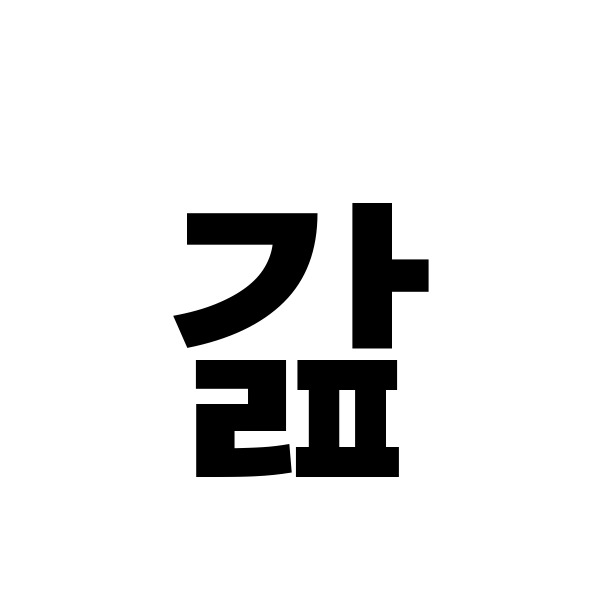
예를 들어 기존 글꼴이 있다면
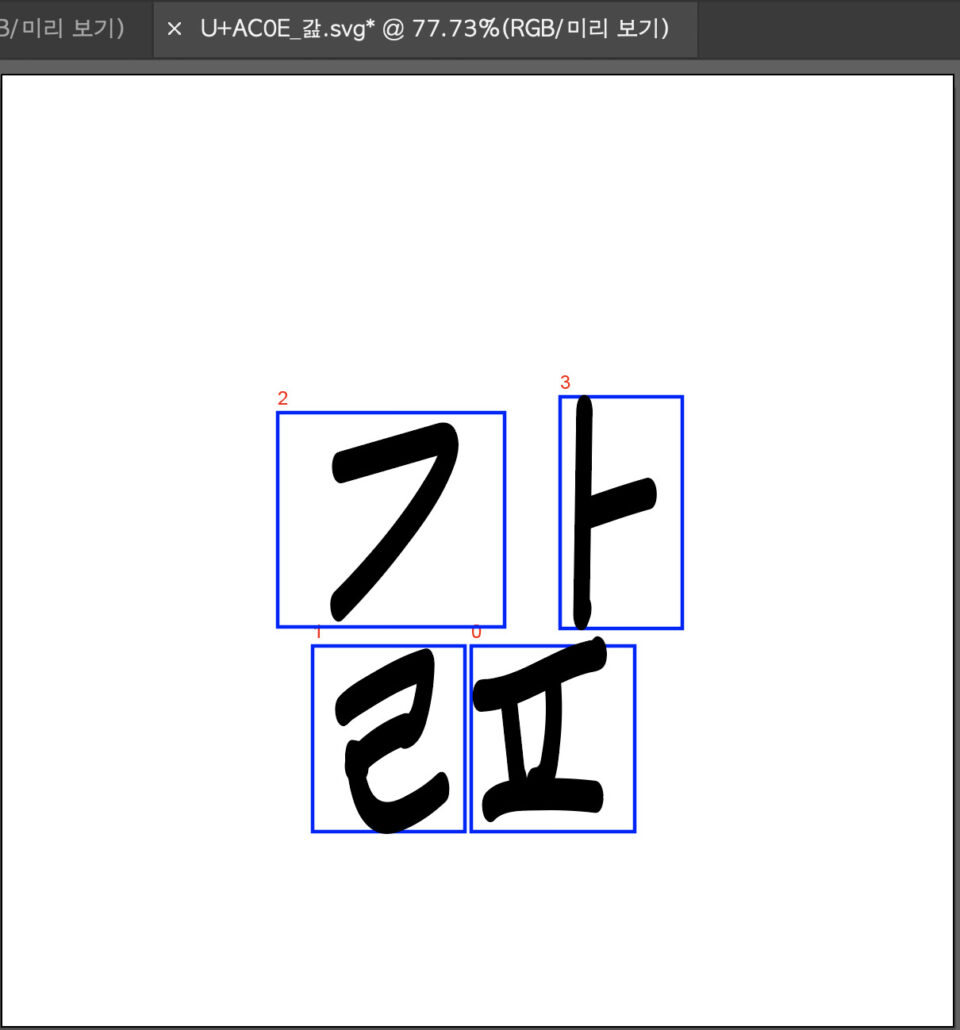
글꼴의 레이아웃에 초성, 중성, 종성을 그려주면 폰트가 생성됩니다.
벡터로 그린 것 이외에 다른 방식도 가능합니다. 그냥 비트맵인 포토샵이나 코믹스튜디오에서 작업하면 이미지를 벡터화하여 폰트로 만들 수 있습니다.
집중해서 기능적인 부분을 마무리하고 아이패드 프로크리에이터에서 개별 폰트의 레터링을 제작할 수 있는 템플릿을 그대로 한글폰트로 만들 수 있게 하면 되지 않을까 합니다.
초성, 중성, 종성만 그리면 다양한 레이아웃으로 바로 폰트 1000개 가이드폰트 및 템플릿을 만들 수 있습니다. GPU가 필요합니다. 제 머리로는 이제 한계예요 ?!?